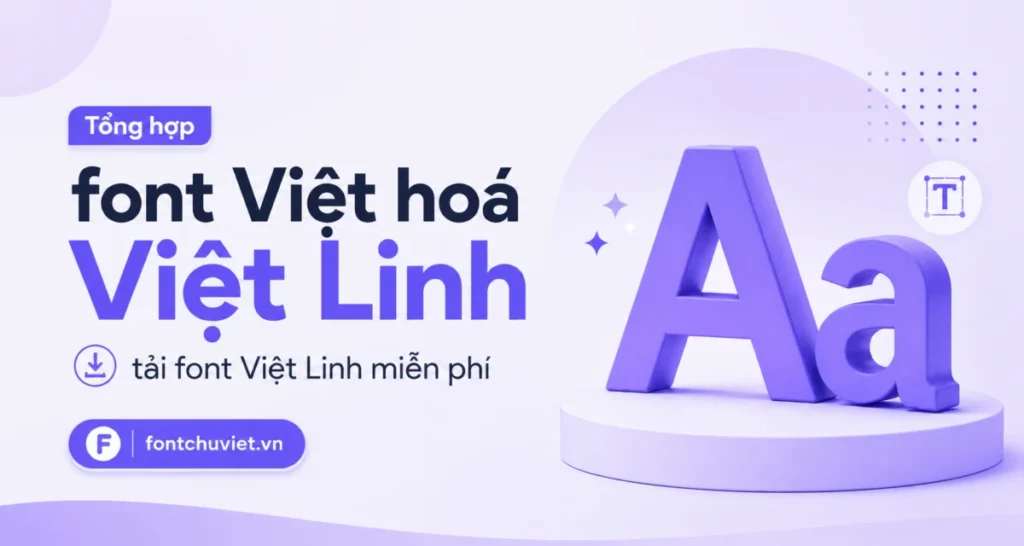
Tổng hợp font Việt hoá Việt Linh, tải font Việt Linh miễn phí
Nếu bạn đang tìm kiếm những bộ font Việt hóa Việt Linh đẹp, đầy đủ dấu tiếng Việt và dễ sử dụng trong thiết kế, thì đây là bài viết dành cho bạn.
Các font do Việt Linh Việt hóa thường được tối ưu để hiển thị tiếng Việt tốt hơn, hỗ trợ nhiều kiểu thiết kế khác nhau từ banner quảng cáo, poster, thumbnail, logo cho tới typography hoặc thiết kế mạng xã hội.
Trong bài viết này, bạn sẽ tìm thấy danh sách font Việt Linh miễn phí, các nhóm font phổ biến và cách chọn font phù hợp với từng nhu cầu thiết kế.
Font Việt hóa Việt Linh là gì?
Font Việt hóa Việt Linh là các font chữ đã được xử lý và tối ưu bộ ký tự tiếng Việt nhằm giúp người dùng dễ dàng sử dụng trong công việc thiết kế hoặc học tập.
Điểm quan trọng của font Việt hóa là hỗ trợ đầy đủ dấu tiếng Việt như:
• Ă, Â, Ê, Ô, Ơ, Ư
• Đầy đủ dấu sắc, huyền, hỏi, ngã, nặng
• Khoảng cách dấu cân đối hơn
• Hạn chế lỗi hiển thị khi thiết kế
Nhờ đó, người dùng có thể gõ tiếng Việt thuận tiện hơn mà không cần chỉnh sửa thủ công khi làm banner, poster hoặc typography.
Vì sao nhiều designer thích dùng font Việt Linh?
Một lý do khiến nhiều người tìm font Việt Linh miễn phí là vì sự tiện lợi trong quá trình thiết kế.
Khi font đã được Việt hóa tốt, designer sẽ tiết kiệm được nhiều thời gian xử lý lỗi dấu hoặc chỉnh sửa bố cục chữ.
Một số ưu điểm thường được người dùng yêu thích gồm:
• Hỗ trợ đầy đủ tiếng Việt.
• Dễ sử dụng trong Photoshop, Illustrator, Canva.
• Có nhiều phong cách font khác nhau.
• Phù hợp với thiết kế banner, poster, logo, social media.
• Dễ phối hợp với nhiều layout.
Dù bạn là người mới học thiết kế hay designer lâu năm, việc có sẵn một thư viện font Việt hóa ổn định luôn giúp công việc nhanh hơn.
Font Việt Linh phù hợp với những thiết kế nào?
Tùy vào từng kiểu font, bạn có thể dùng cho nhiều nhu cầu khác nhau.
Ví dụ:
Thiết kế banner và quảng cáo
Các font đậm, nổi bật thường phù hợp cho:
• Banner sale
• Poster quảng cáo
• Thumbnail YouTube
• Thiết kế social media
Ưu tiên font dễ đọc, nổi bật và có độ tương phản tốt.
Typography và ảnh quote
Các font viết tay hoặc font có cá tính thường phù hợp với:
• Ảnh quote truyền cảm hứng
• Thiết kế typography
• Thiệp, card, hình ảnh cảm xúc
Những font này giúp nội dung có cảm xúc và tạo điểm nhấn tốt hơn.
Logo và nhận diện thương hiệu
Nếu làm logo hoặc branding, bạn có thể ưu tiên:
• Font sans serif hiện đại
• Font serif cao cấp
• Font display cá tính
Một font đẹp đôi khi có thể quyết định phần lớn cảm giác thương hiệu.
Cách chọn font Việt Linh phù hợp
Không nên chọn font chỉ vì “nhìn đẹp”.
Một số nguyên tắc đơn giản:
Thiết kế nhiều chữ → chọn font dễ đọc.
Thiết kế tiêu đề lớn → chọn font nổi bật hơn.
Thiết kế cao cấp → ưu tiên serif hoặc font thanh lịch.
Thiết kế trẻ trung → dùng handwritten hoặc display.
Tổng hợp font Việt hóa Việt Linh đẹp nên có
Dưới đây là danh sách tổng hợp các font Việt hóa Việt Linh đẹp, dễ dùng, hỗ trợ đầy đủ dấu tiếng Việt và phù hợp cho nhiều nhu cầu thiết kế khác nhau.
Việc sở hữu một bộ font Việt Linh miễn phí đầy đủ dấu tiếng Việt sẽ giúp designer tiết kiệm thời gian, hạn chế lỗi font và tăng chất lượng thiết kế đáng kể.
Nếu thường xuyên làm banner, poster, logo, social media hoặc typography, đừng quên lưu lại những bộ font Việt hóa Việt Linh phù hợp để sử dụng lâu dài trong công việc thiết kế.